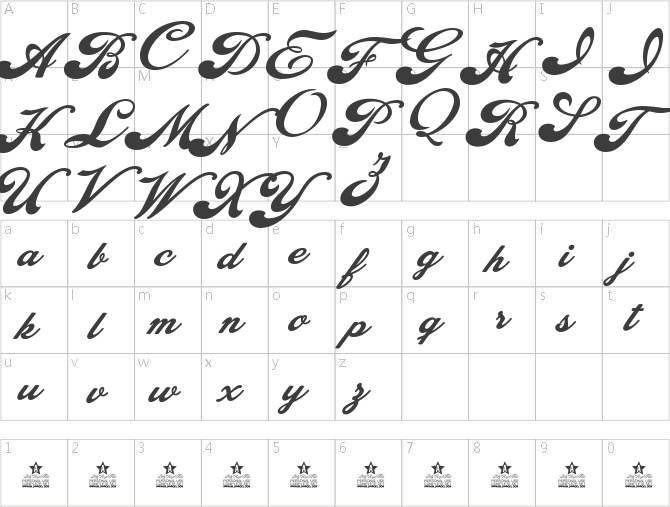
Bobbers Personal Use 詳情頁
字體名稱: Bobbers
Bobbers Personal Use
Bobbers Personal Use介紹
Bobbers Personal Use字體字庫是一款讓人賞心悅目、百看不厭的英文字體,適合各類廣告和產品包裝設計應用,字體大小0.04MB,格式為ttf字體,上傳用戶是翰池書法,作者/版權方為未知
Bobbers Personal Use效果圖